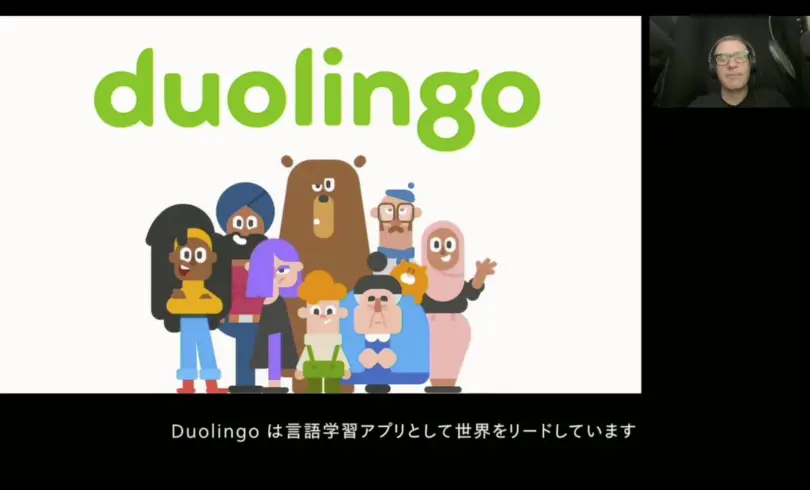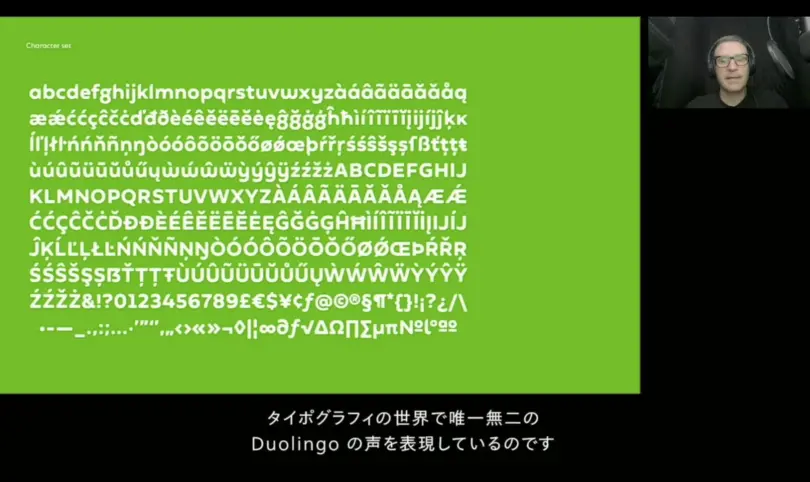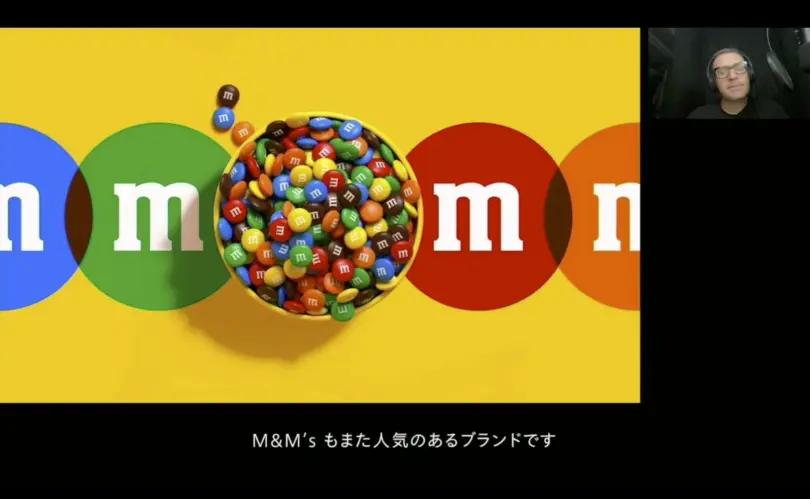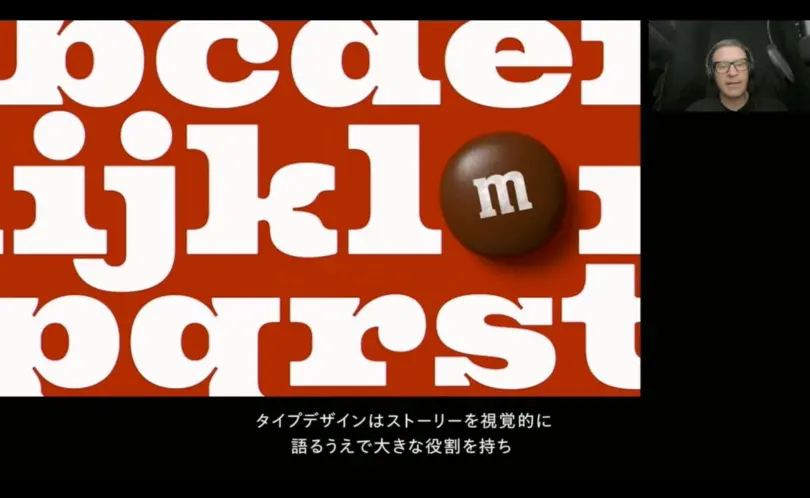
タイポグラフィによる自己実現
Type& 2022 Day 2 Session 1 - Monotype による大手企業のコーポレートフォント制作事例を交えながら、タイポグラフィや、既成フォント、企業独自のフォント制作に至るまでを解説。
Type& 2022 Day 2、Session 1 は、Monotype クリイティブタイプディレクター、Charles Nix(チャールズ・ニックス)プレゼンテーションです。Nixは、ニューヨークを中心に活躍するクリエイティブタイプディレクター、タイポグラファーで、タイポグラフィ業界の発展を目指す国際団体、Type Directors Club の名誉会長でもあります。このセッションでは、既存のフォントを使用することから、企業が独自のフォントを持つことまでを段階的に分析しながら、Monotype が近年手掛けた大手企業のコーポレートフォントの実例を紹介しました。
メッセージを文字で伝えることについて
Charles Nix は、「書体とは著者の考えをエンコード(符号化)し、それをデコード(解読)して受け取る役割と持つ」と述べています。その例として、歴史学者、地理学者のヘロドトスについて解説。2500年前にヘロドトスの思想が文字に書き起こされたことにより、現在でもその思想を書籍で読むことができると説明しました。つまり、本を開けば、2500年前のメッセージを解読できるということです。
昔は印刷して本の形でメッセージを伝えていましたが、今では数百マイルの空間を越えて、携帯電話で数秒でメッセージの伝達が可能になりました。現在では、スマートフォンの中で組版、印刷、校正編集、製本、翻訳、輸送のすべてが行われているのです。スマートフォンが組版職人や印刷機の役割を果たし、誰もがタイポグラファーになり得るわけです。人間には互いの考えをやりとりして交流したいという根源的な欲求があり、スマートフォンはその欲求に瞬時に応えることができると Nix は説明します。
人間の欲求の段階を表したピラミッド図
人間の根源的な欲求について、米国の心理学者マズローが構築したモデル図をもとに解説。(ピラミッドの下から上へ次のような段階に分類)
1. Physiological(生理的欲求)
2. Security(安全への欲求)
3. Love and belonging(愛と帰属への欲求)
4. Esteem(尊敬への欲求)
5. Self-actualization(自己実現への欲求)
食欲など生存に必要な「生理的欲求(1)」がある程度満たされると、より高度な「安全への欲求(2)」を持ち始めます。その次の「愛と帰属(3)」は、付き合いや友情、所属、団体との関係など、社会的な欲求や愛を受け取る力。さらに次の段階では、自尊心や他者からの尊敬、達成感や尊厳、主体性など「尊敬への欲求(4)」を求めます。そして最後は、自分の可能性を最大限生かし、創造力を働かせ、他者の向上を助ける「自己実現への欲求(5)」です。
デザインをする上で、この人間の欲求を理解する必要があると Nix は述べます。デザイナーやタイポグラファーは顧客の欲求に共感し、自身の過去と他者の現在の体験を結びつける力が必要だと言います。
タイポグラフィ的欲求
「人間の根源的な欲求」を説明した後、同じピラミッド図を用いて「タイポグラフィ的欲求」を解説(ピラミッドの下から上へ次のような段階に分類)。
1. Font functionality(書体の機能性)
2. Font security(書体の安全性)
3. Typographic Love and belonging(タイポグラフィ的帰属)
4. Typographic esteem(タイポグラフィ的差別化)
5. Typographic actualization(タイポグラフィ的自己実現)
一番下のレベルは「書体の機能性(1)」。「伝える」という文字の機能が重要視されます。その次は「書体の安全性(2)」。正しい許諾を得てライセンスされた書体を使うことが重要になります。その先は、書体の様々な違いを理解し、使いこなせる段階。タイポグラフィについて語り合える仲間を見つけることによって、そのコミュニティに帰属する喜びを見出し、「タイポグラフィ的帰属(3)」へと移行します。そして、その先にあるのは、「タイポグラフィ的差別化欲求(4)」。「私は他と違う。既存の書体には表現できない素質がある」という宣言です。
ピラミッド図の一番上にあるのが「タイポグラフィ的自己実現(5)」で、他者承認と自己承認の2種類があります。タイポグラフィが自分のメッセージを代弁してくれると感じ、それが相手にも伝わり、理解されていることを実感できる段階です。
タイポグラフィを尊重することで生まれるのは、グラフィックデザインの持つ力や作品が完成するまでの奥深いプロセスへの理解、言語やメッセージのスタイルの重要性の理解。そして、デザインの影響力を最大限に発揮するには、発信者と受信者のコミュニケーションに合わせて独自に仕立てるのが最適と Nix は言います。カスタム書体を作ることもこの段階に相当します。
Monotype で手掛けた事例紹介
カスタム書体の事例として、Monotype で手掛けた2つの事例を紹介しました。
Duolingo
言語学習アプリ Duolingo の事例です。Duolingo は言語教育のゴールに対し、1. 教育をパーソナライズする、2. 広くアクセスできるようにする、3. 楽しく学べるようにする、という競合他社とは違うアプローチをしています。こうした特徴を反映して、Duolingo の声を表現したカスタム書体を制作。タイポグラフィの重要性に気づくきっかけになり、競合他社と差別化しました。Duolingo は自社の価値を知り、ブランドに対する誇りを持っており、カスタム書体はこのブランドの価値をさらに高めています。
M&M’s
ブランディングエージェンシー JKR と M&M’s の書体を制作。書体の制作は JKR のチームによるリブランディング計画の中核でした。書体は、ストーリーを視覚的に語る上で大きな役割を持ち、活気を取り戻したブランドに唯一無二の声を与えました。
書体によるブランディング
書体とブランディングの目的、ブランドが存在する意味は、みんなが帰属意識を持てるような、よりインクルーシブな世界を作ることだとNix は説明します。インクルーシブな世界を目指すことは、マズローのピラミッド図の頂点に相当します。これはタイポグラフィの枠を超えたタイポグラフィによる自己実現で、より大きな目標を達成することができるのです。
タイポグラフィ的自己実現とは、自分の目的を信じて行動することです。それはタイポグラファーの世代間をつなぎ、タイポグラフィを教え、よりよい未来を創造することでもあります。タイポグラフィは新しいデザインについての会話を生み、タイポグラフィが私たちを上へと押し上げることで、コミュニケーションは活性化され、文化を発展させる身近なツールとなります。私たちにとってタイポグラフィはなくてはならない大切な存在である、とNix は締め括りました。
Q & A 質疑応答
ピラミッドで表されているヒエラルキーについて、ある段階から次の段階への移行は自然に行われているのでしょうか? または、何らかの具体的な行動や活動により行われるのでしょうか?
Nix:マズローによれば、ある段階の欲求がほぼ満たされたことがきっかけとなり、次の段階へ移行するそうです。ブランドや企業、個人がタイポグラフィの機能的役割を達成すると、次の段階へ移行します。例えば、ライセンスがきっかけの場合もあれば、違法コピーのフォントを使っていたことによる影響や、タイポグラフィに関する記事を見かけて気づくこともあるでしょう。コンプライアンスのチェック中に気づいたり、読み込みの遅いウェブページやテキストの修正作業中にライセンスの重要性に気づいたりすることもあります。すべての欲求を満たすことは次のレベルへと進む一つの方法ですが、これで欲求が消えるわけではありません。
ヒエラルキーの2(Security)から3(Love and Belonging)は大きなジャンプだと思いますが、どのようなファクターにより移行するのでしょうか?
Nix:この大きなジャンプをする要因はきっと数十はあるでしょう。タイポグラフィがブランドを統一する大きな力となり、内部・外部の両方の視点からブランドの価値を高めることや投資に対して大きな利益を得られることに気づくことも要因の一つでしょう。タイポグラフィへの投資はブランドの価値を高め、利益につながります。タイポグラフィの基本を理解する社員が組織を動かすこともあります。
あるいは、利益の追求の結果ということもあるでしょう。価値を理解した上で書体を購入したり、書体の持つ効果に気づいたり、興味を持ったり、尊重したりします。書体を購入するからには何かが得られるに違いないと考え、その何かを好奇心旺盛な人々は知りたくなります。
Duolingo 以外にこれまで携わった事例を教えてください。また、その中でも特に印象に残ったプロジェクトはありますか?
Nix:Monotype が最近手掛けた配送会社 Evri とのプロジェクトもその一つです。バイタリティがあり、いろんな顔つきを持つロゴは顧客やサービスの多様性を表しています。Evri はただの企業名ではなく、すべての顧客や場所、お届け物に対するブランドの声を表現しているのです。
サウスウェスト航空もタイポグラフィを通じてブランドの声を表現しています。サウスウェスト航空の使命は「人生に大切なものと人をつなげる」、そしてビジョンは「世界一効率的で、収益性が高く、愛される航空会社になること」です。これらはブランドのタイポグラフィや色味、視覚的言語に反映されていて、フレンドリーで柔らかく、スマートな印象を与えています。
小林章から一言
Nix の言うピラミッドの頂点、タイポグラフィ的自己実現というのは日本ではType&の1日目で紹介した2つの事例のことだと思いました。ピラミッドの頂点に到達する企業が日本でも増えているというのは心強いと思います。他社とは違う独自の声を持つという差別化ができるだけではなくて、社員みんながブランドに誇りを持つことができる、書体がブランドを作る役割を持っている、そんなことを知っている方たちです。1日目にご登壇いただいたブリヂストンの酒本さんや、いすゞ自動車の杉浦さんのように、書体の価値がわかって、企業の自己実現に向けて引っ張ってくれる人が日本でも出てくるのではないかと思います。